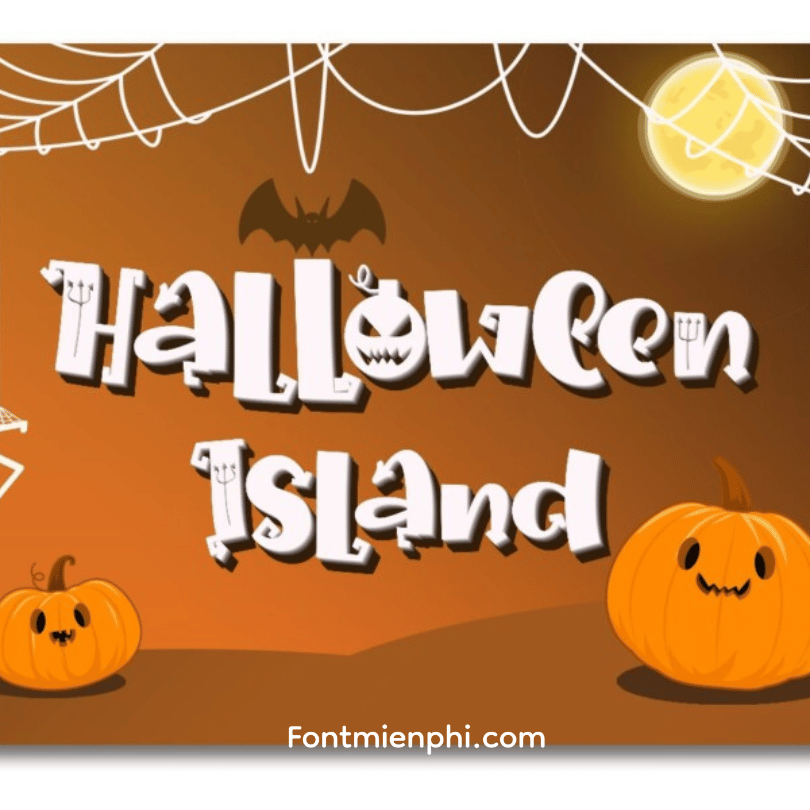
Việt hóa font Sayuri Halloween Island
Việt hóa font Sayuri Halloween Island – Phông Chữ Ma Mị Đảo Halloween
Sayuri Halloween Island là bộ font chữ Việt hóa độc đáo mang đậm không khí lễ hội ma quái, với những đặc điểm nổi bật:
PHONG CÁCH THIẾT KẾ:
• Lấy cảm hứng từ hòn đảo Halloween bí ẩn
• Kết hợp tinh tế giữa nét chữ mềm mại và chi tiết kinh dị
• Hiệu ứng bóng ma và ánh trăng huyền ảo
TÍNH NĂNG ĐẶC BIỆT:
✔ Bao gồm 4 biến thể: Regular, Bold, Shadow và Outline
✔ Tích hợp 50+ glyph đặc biệt và ký tự Halloween
ỨNG DỤNG SÁNG TẠO:
• Thiết kế bộ nhận diện lễ hội Halloween
• Làm poster phim kinh dị, truyện ma
• Thiết kế bao bì kẹo Halloween
• Tạo logo quán café theme ma quái
• Làm thiệp mời tiệc hóa trang
Halloween Island là một font decorative cho dịp Halloween, thiết kế bởi Thomas Aradea, và phát hành bởi Letterara tại Myfonts. Halloween Island có nhiều ký tự thay thế và những họa tiết trang trí thích hợp với không khí mùa Halloween như mạng nhện, dơi, bóng ma… Trong một dịp như thế này mình thường minh họa bằng dòng chữ “Happy Halloween”, nhưng nay chắc là không happy được rồi. Mà font thì cũng đã Việt hóa, nên mình vẫn đăng lên cho mọi người thưởng thức nhé.